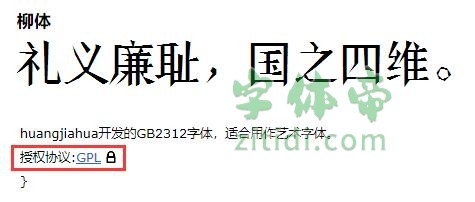
柳体是2006年的一款GB2312字体,这款字体虽然命名柳体,但跟我们印象的柳体很不一样。这款字体虽然字符数比较少,但字形很有特点,有点刻字的味道。并且打印出来后的阅读效果不错,在生僻字不多的书面材料(例如领导讲话稿)里用应该很合适。按照原作者的说法,这是一款用算法模拟生成的字体。点阵来源为GPL字体 intlfonts-1.2.1,使用了其中的24pix GB2312字型。
“柳体”是一款书写很新颖的字体,字体大方,适合各种设计作品使用!欢迎下载!